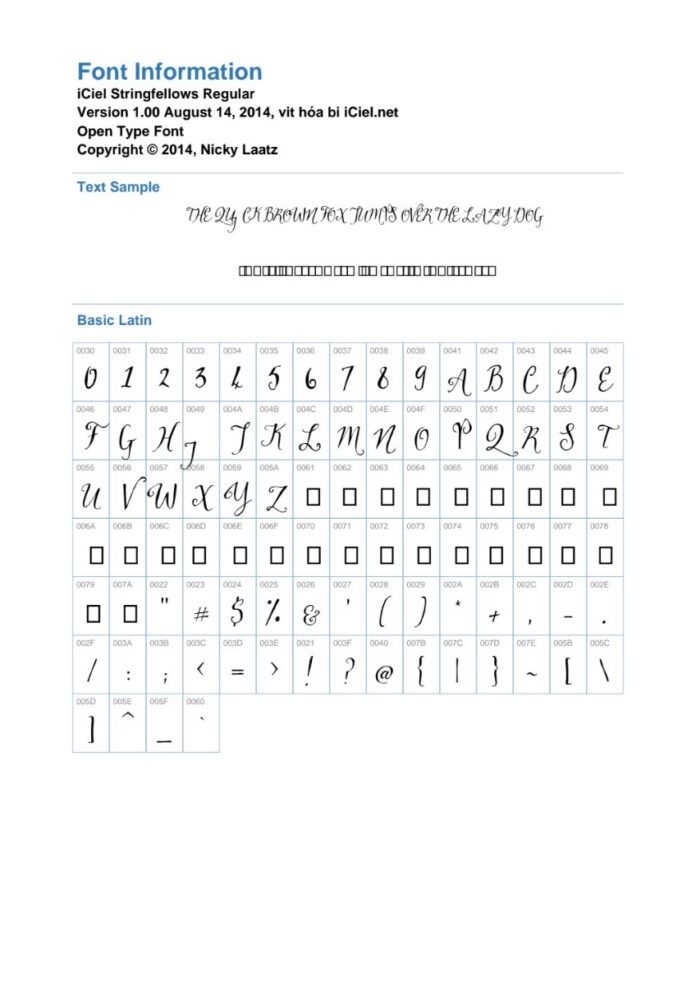
Font Chữ Stringfellows Đẹp Mắt
Trong thế giới thiết kế đồ họa, việc lựa chọn font chữ phù hợp có thể tạo nên sự khác biệt lớn cho tác phẩm của bạn. Font chữ không chỉ truyền tải thông điệp mà còn thể hiện cá tính và phong cách. Hôm nay, Poster.vn hân hạnh giới thiệu đến bạn một tài nguyên font chữ đặc biệt: Stringfellows – một lựa chọn hoàn hảo cho những ai tìm kiếm sự tinh tế, mềm mại và độc đáo.
Giới thiệu về Font Stringfellows
Font Stringfellows là một kiểu chữ viết tay (script font) được thiết kế bởi Nicky Laatz, ra mắt vào năm 2014. Với những đường nét uyển chuyển, mềm mại và phong cách tự nhiên, Stringfellows mang đến cảm giác chân thực như được viết bằng tay. Đây là một font chữ OpenType, tương thích rộng rãi với nhiều phần mềm thiết kế và hệ điều hành khác nhau, đảm bảo tính linh hoạt cao trong quá trình sử dụng.
Đặc điểm nổi bật của Font Stringfellows
• Phong cách viết tay tự nhiên: Stringfellows nổi bật với các ký tự được thiết kế mô phỏng chữ viết tay, tạo cảm giác gần gũi, cá nhân và đầy nghệ thuật.
• Đường nét mềm mại, uyển chuyển: Mỗi ký tự đều được chăm chút tỉ mỉ với các đường cong mượt mà, mang lại vẻ đẹp thanh lịch và tinh tế.
• Tính linh hoạt cao: Phù hợp với nhiều loại hình thiết kế khác nhau, từ thiệp mời, logo, bao bì sản phẩm đến các ấn phẩm truyền thông xã hội.
• Dễ đọc: Mặc dù là font viết tay, Stringfellows vẫn đảm bảo khả năng đọc tốt, không gây khó khăn cho người xem.
Ứng dụng của Font Stringfellows trong thiết kế
1. Thiết kế thiệp mời và thiệp chúc mừng
Stringfellows là lựa chọn lý tưởng cho các loại thiệp mời cưới, thiệp sinh nhật, thiệp chúc mừng các dịp lễ. Phong cách viết tay của font chữ này sẽ làm tăng thêm sự ấm áp, cá nhân và trang trọng cho mỗi tấm thiệp. Imagine một thiệp cưới với tên cô dâu chú rể được viết bằng Stringfellows – chắc chắn sẽ gây ấn tượng mạnh mẽ.
2. Thiết kế logo và nhận diện thương hiệu
Đối với các thương hiệu muốn thể hiện sự sáng tạo, tinh tế và gần gũi, Stringfellows có thể là một phần quan trọng trong việc xây dựng logo và bộ nhận diện. Đặc biệt phù hợp với các ngành nghề như thủ công mỹ nghệ, thời trang, làm đẹp, quán cà phê hay các dịch vụ cá nhân hóa.
3. Thiết kế bao bì sản phẩm
Một bao bì sản phẩm đẹp mắt, độc đáo sẽ thu hút sự chú ý của khách hàng. Sử dụng Stringfellows trên bao bì có thể tạo ra cảm giác sang trọng, thủ công và chất lượng cao, đặc biệt là với các sản phẩm handmade, mỹ phẩm tự nhiên hoặc thực phẩm cao cấp.
4. Thiết kế ấn phẩm truyền thông xã hội
Trong thời đại số, các bài đăng trên mạng xã hội cần phải nổi bật để thu hút tương tác. Stringfellows có thể giúp bạn tạo ra các hình ảnh, banner, quote graphic độc đáo, mang đậm dấu ấn cá nhân và phong cách riêng, giúp tăng cường sự nhận diện thương hiệu trên các nền tảng như Instagram, Facebook.
5. Thiết kế sách, tạp chí và tiêu đề
Với khả năng đọc tốt và vẻ đẹp nghệ thuật, Stringfellows cũng rất phù hợp để sử dụng làm tiêu đề, phụ đề hoặc các đoạn văn ngắn trong sách, tạp chí, blog. Nó sẽ tạo ra một điểm nhấn thị giác thú vị, giúp người đọc không bị nhàm chán.